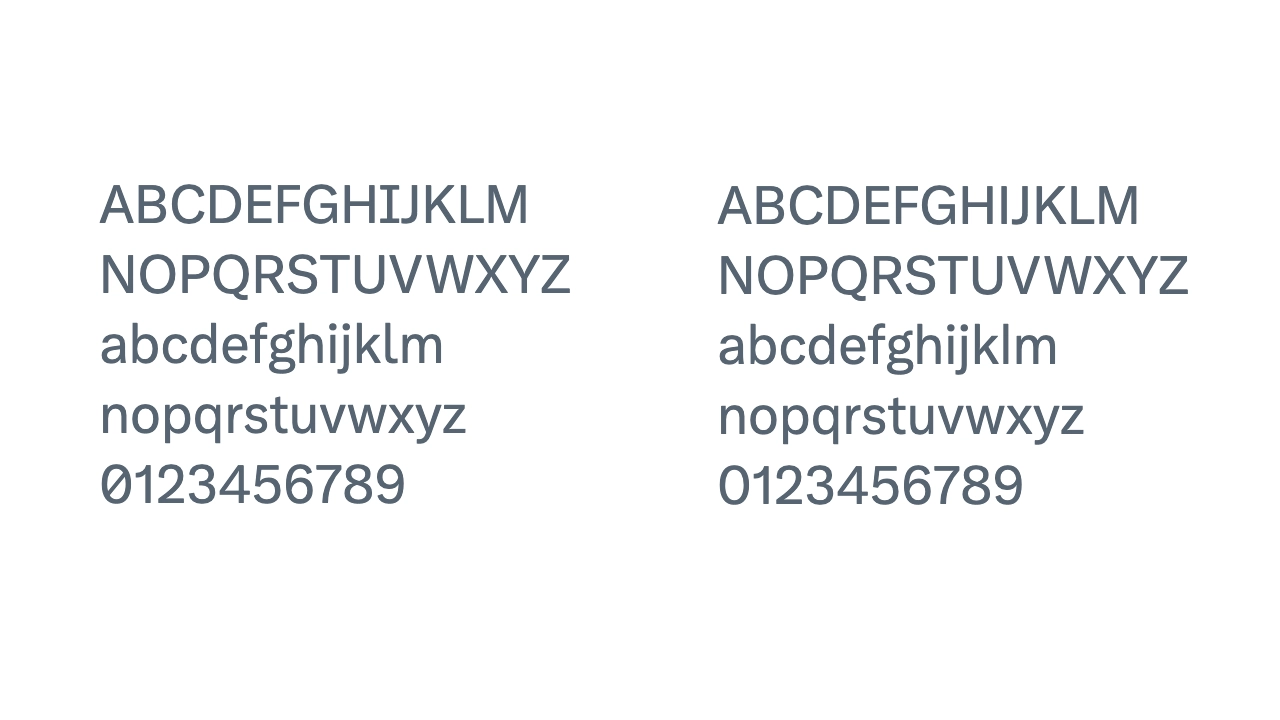
Twitter gözünüze farklı geldiyse şaşırmayın: Yazı tipi değişti
Elon Musk'ın yeni oyuncağı Twitter, sahte ve birbirine benzer hesapları platformdan engellemek için yazı tipinde değişikliğe gitti.
Bugün sosyal medya platformuna giriş yapan Twitter kullanıcıları, uzun süredir kullanılan yazı tipinin değiştiğini fark etti. Çok az sayıda kullanıcının fark ettiği yeni yazı tipi, Twitter'da eskiden kullanılan tipografiye büyük oranda benzerlik gösteriyor. Sadece birkaç harf karakterinde belli olan bu yazı tipi değişikliğinin neden yapıldığı açıklanmasa da, bazı analistler, konuyla ilgili düşüncelerini dile getirdi ve bu değişikliğin arkasında yatan nedeni öne sürdü.
Twitter kullanıcıları bugün platforma giriş yaptıklarında masaüstü sürümünde bazı yazı tipi değişiklikleri fark ettiler. Alanında uzman olmayan kişilerin dışında çok az kişinin farkına vardığı bu yazı tipi değişikliğinin,  sahte ve birbirleriyle benzerlik taşıyan hesapların önüne geçmek için yapıldığı iddia edildi. Henüz bu konuyla ilgili bir açıklama yapmayan Twitter,  yeni yazı tipi değişiklikleriyle birlikte büyük i ve küçük l harfleri için birbirinden ayırmayı sağlayacak. Ek olarak 0 sayısı ve büyük o harfinin de birbirinden ayrılmasını sağlayacak yeni farklılıklar, platforma sunulan yazı tipinde mevcut olacak.
Platformda kullanıma giren bu gibi ufak farklılar, Twitter’da sahte hesaplar oluşturmayı engelleyecek.